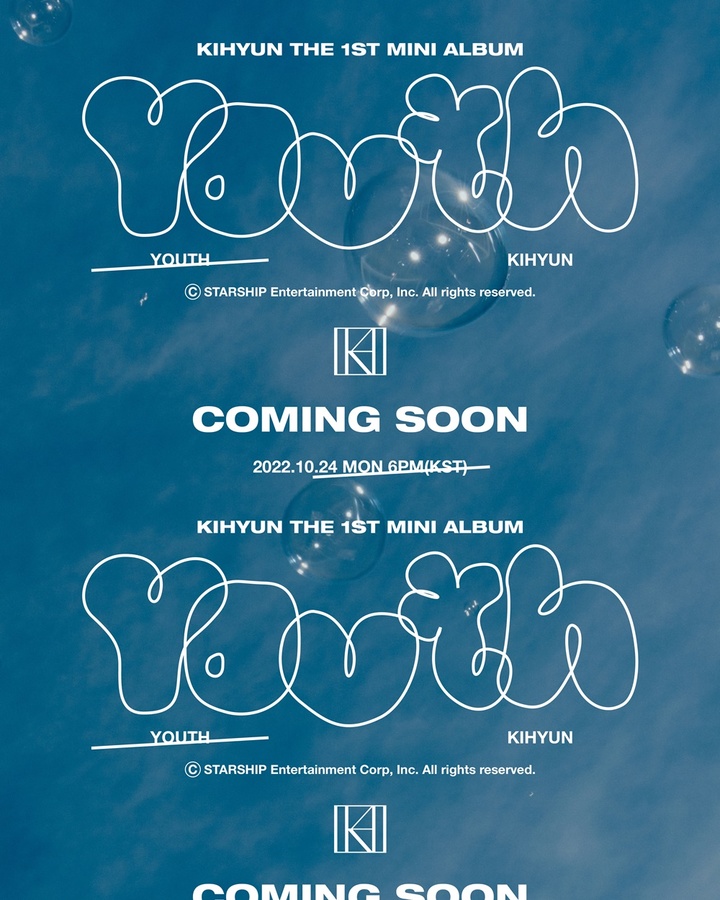
이것도 폰트일까요 a01*** 2022.10.19 사진에 youth 이것도 폰트일까요 댓글 0 등록 gad*** 레터링이요 2022-10-20 답글 달기 오타대마왕 찾아봤는데...음..아마도 라인으로 그려진 레터링 같아요. 2022-10-20 답글 달기 댓글 더보기 쉽고 빠르게 가장 비슷한 폰트를 알고 싶다면? 이미지로 검색하기
레터링이요
찾아봤는데...음..아마도 라인으로 그려진 레터링 같아요.